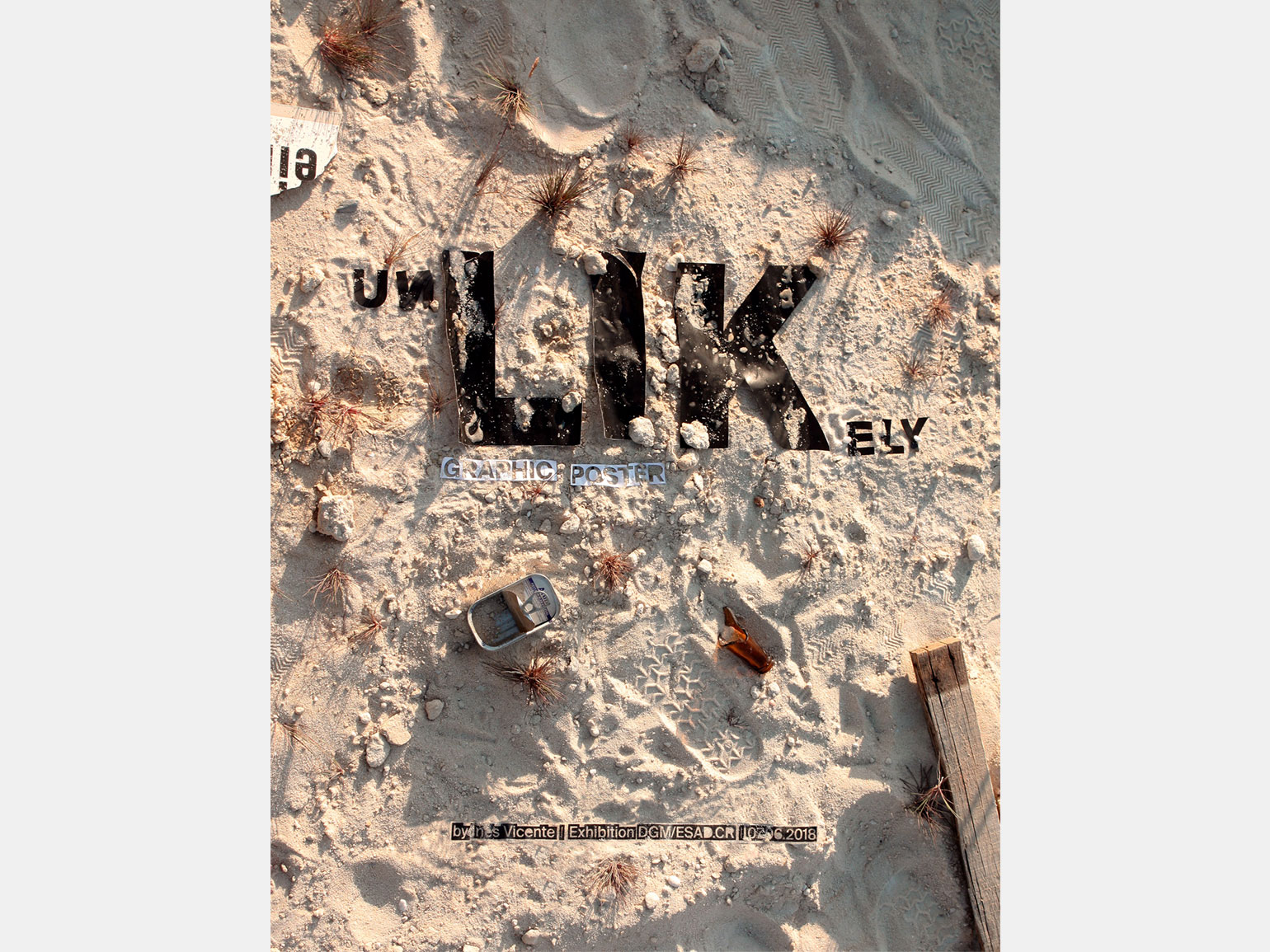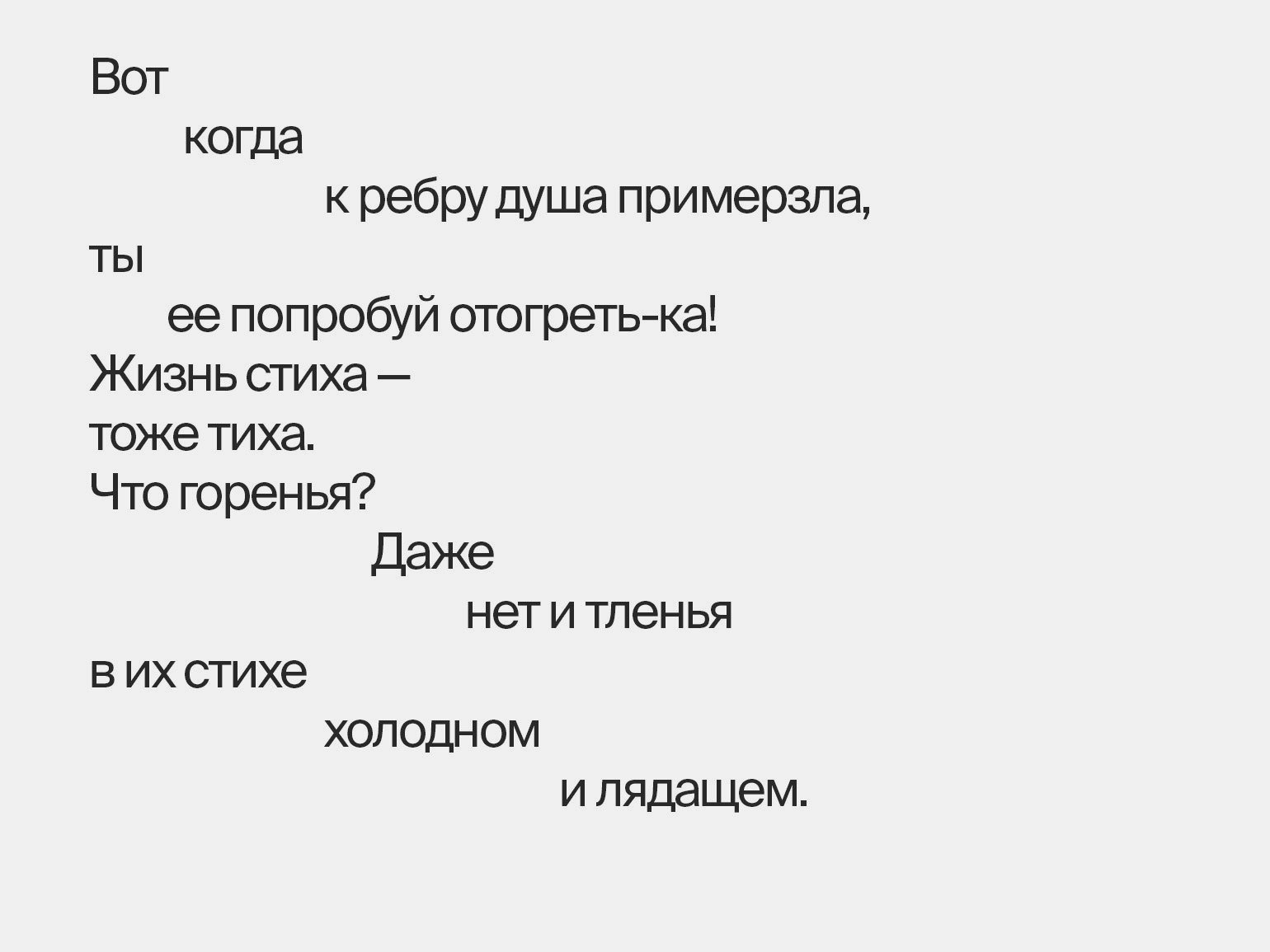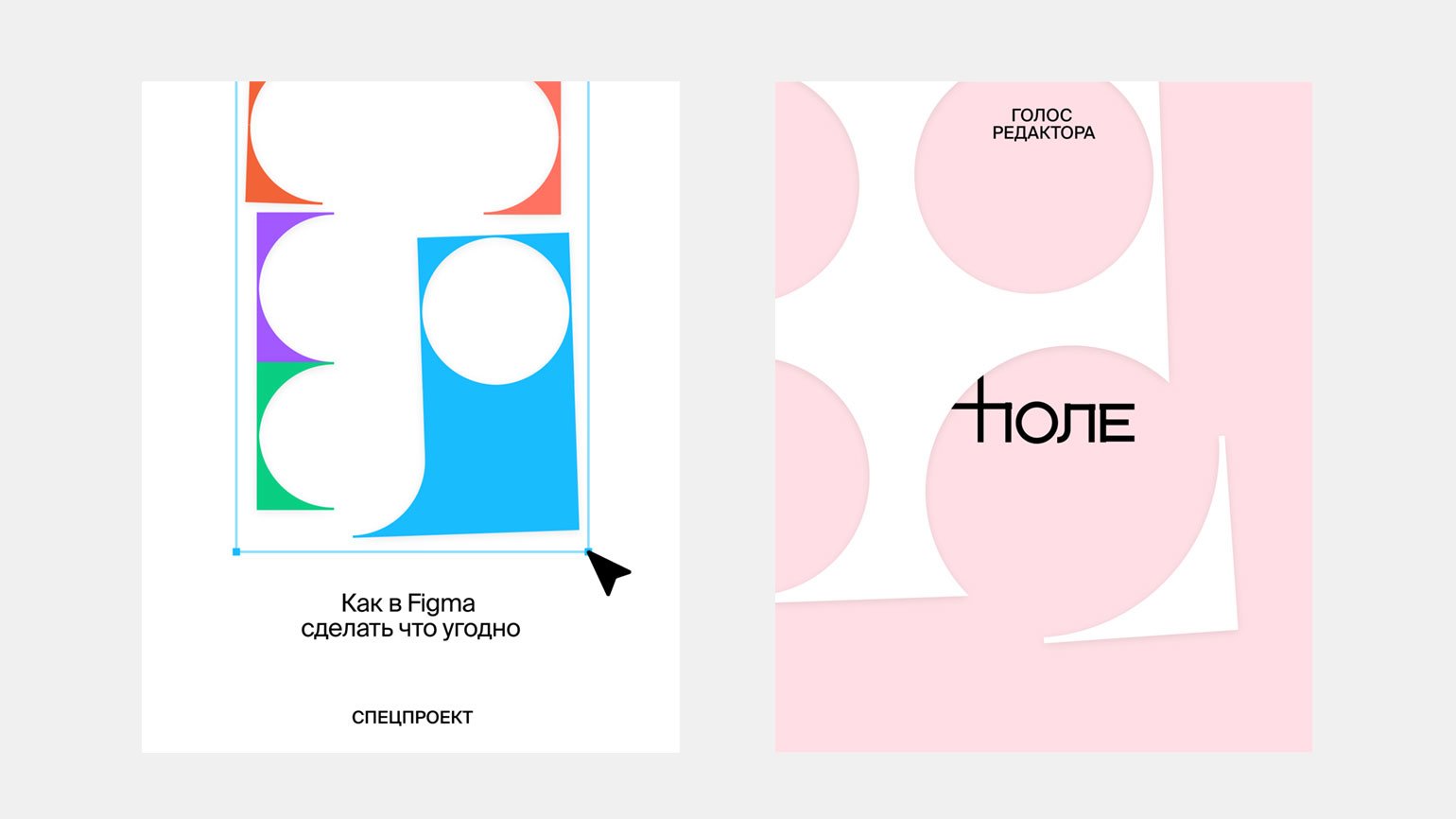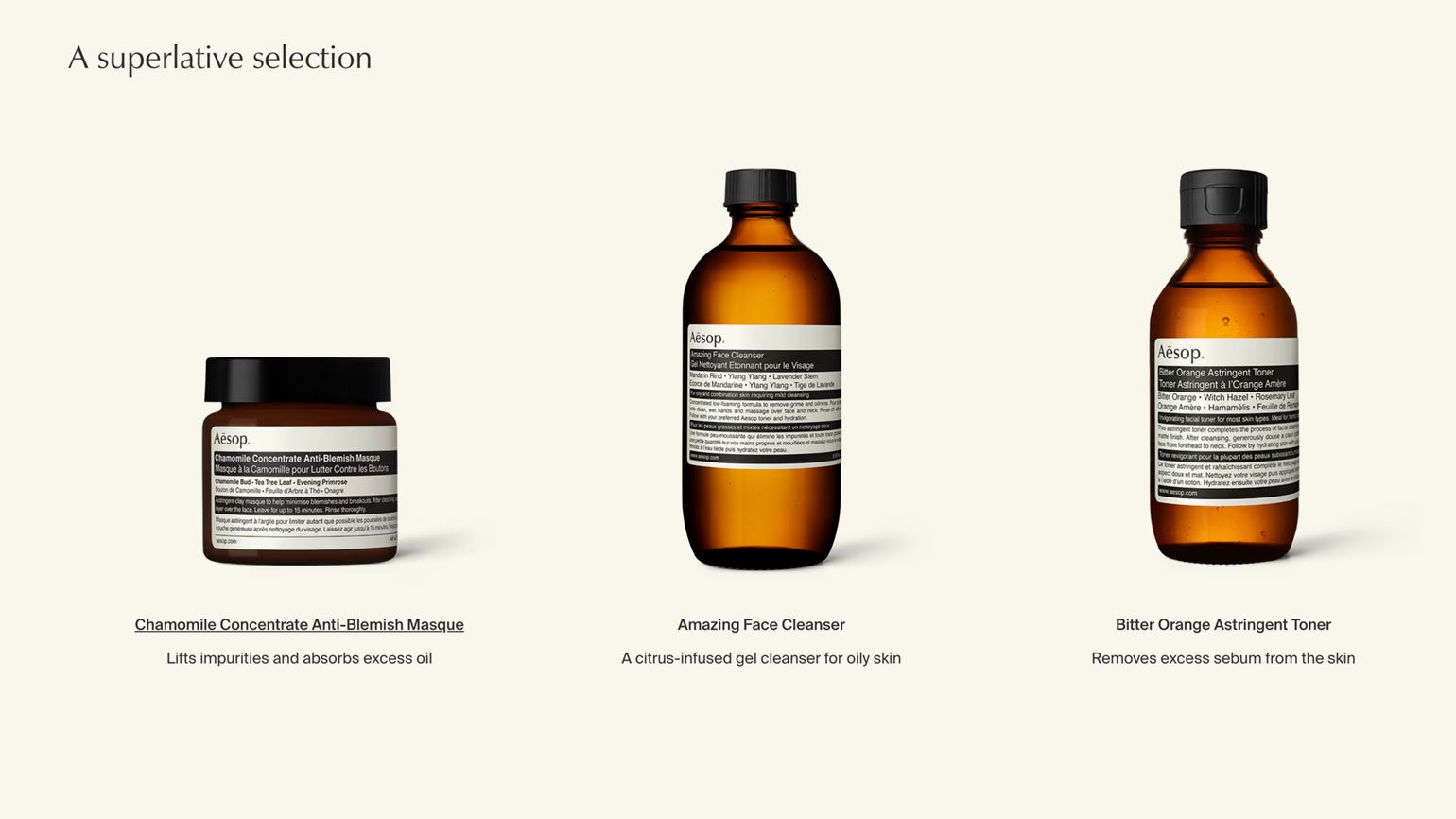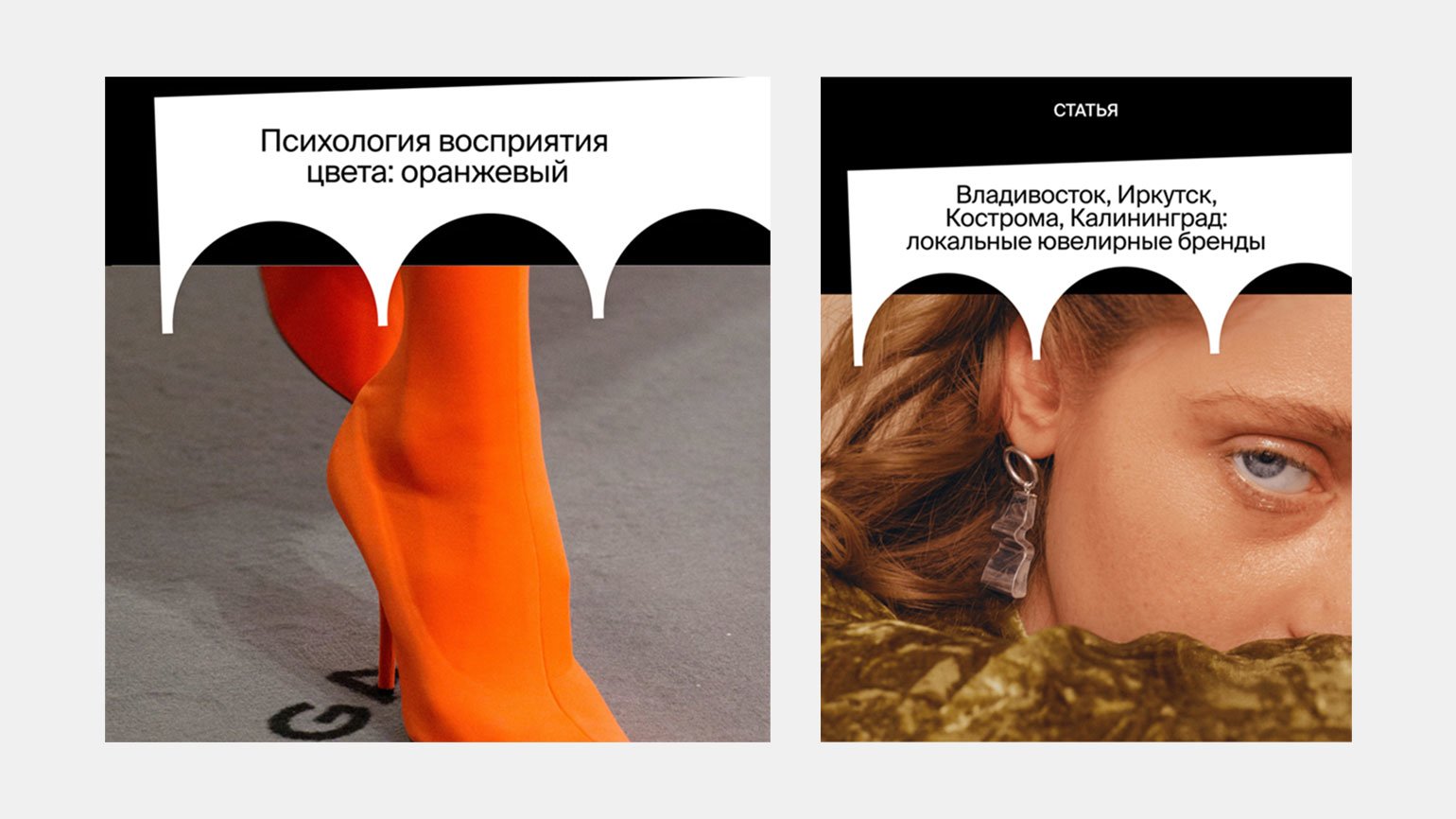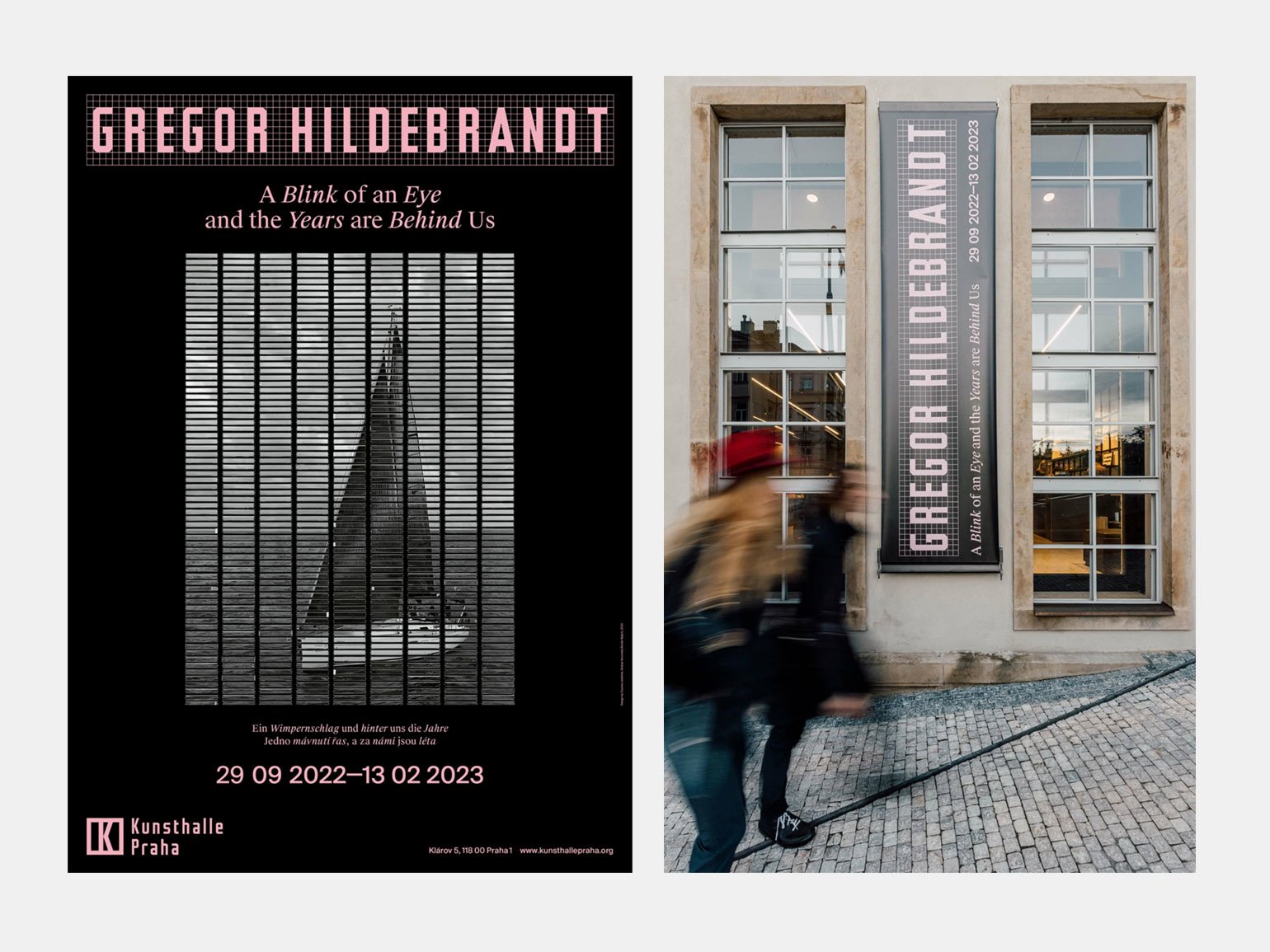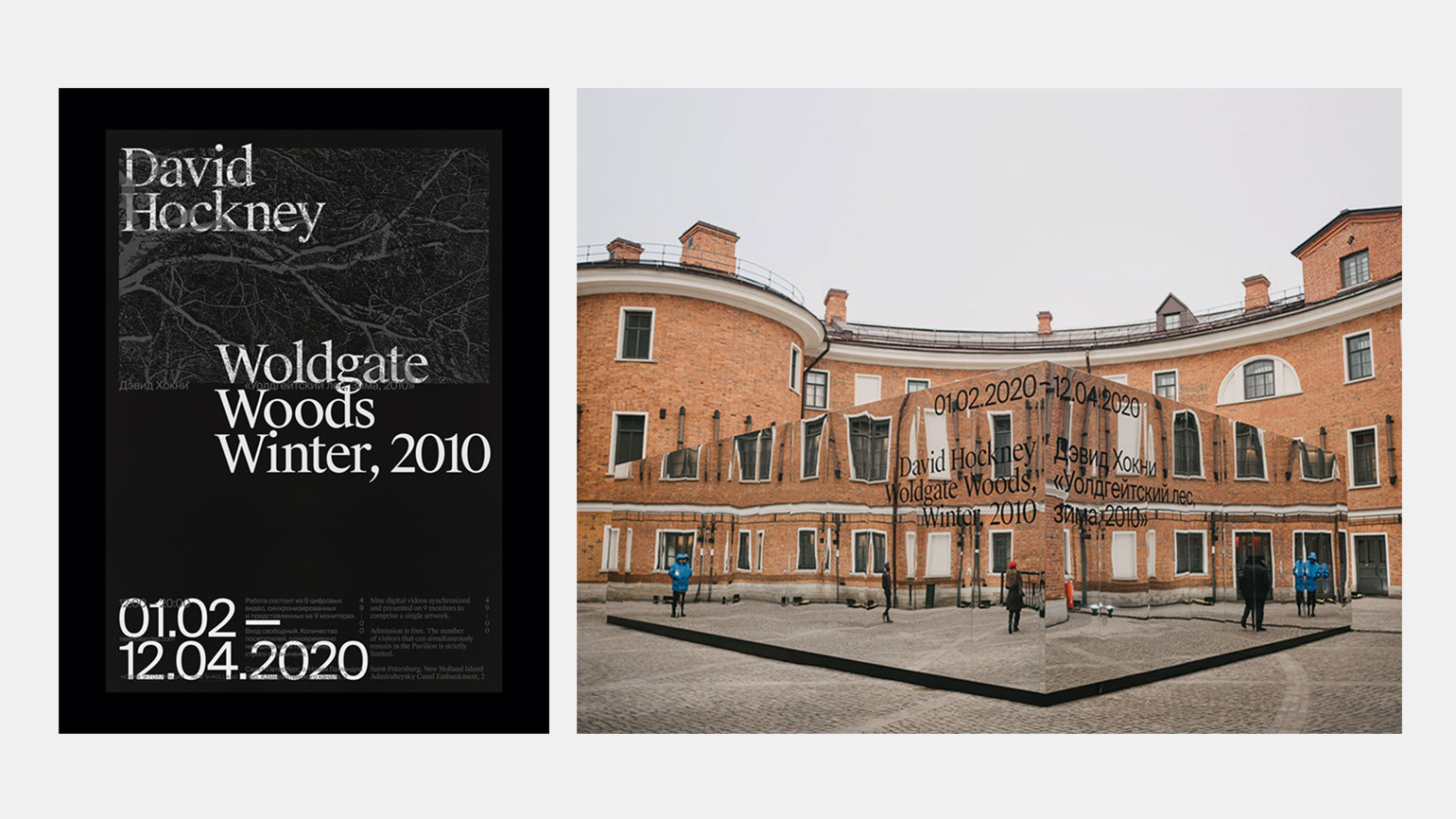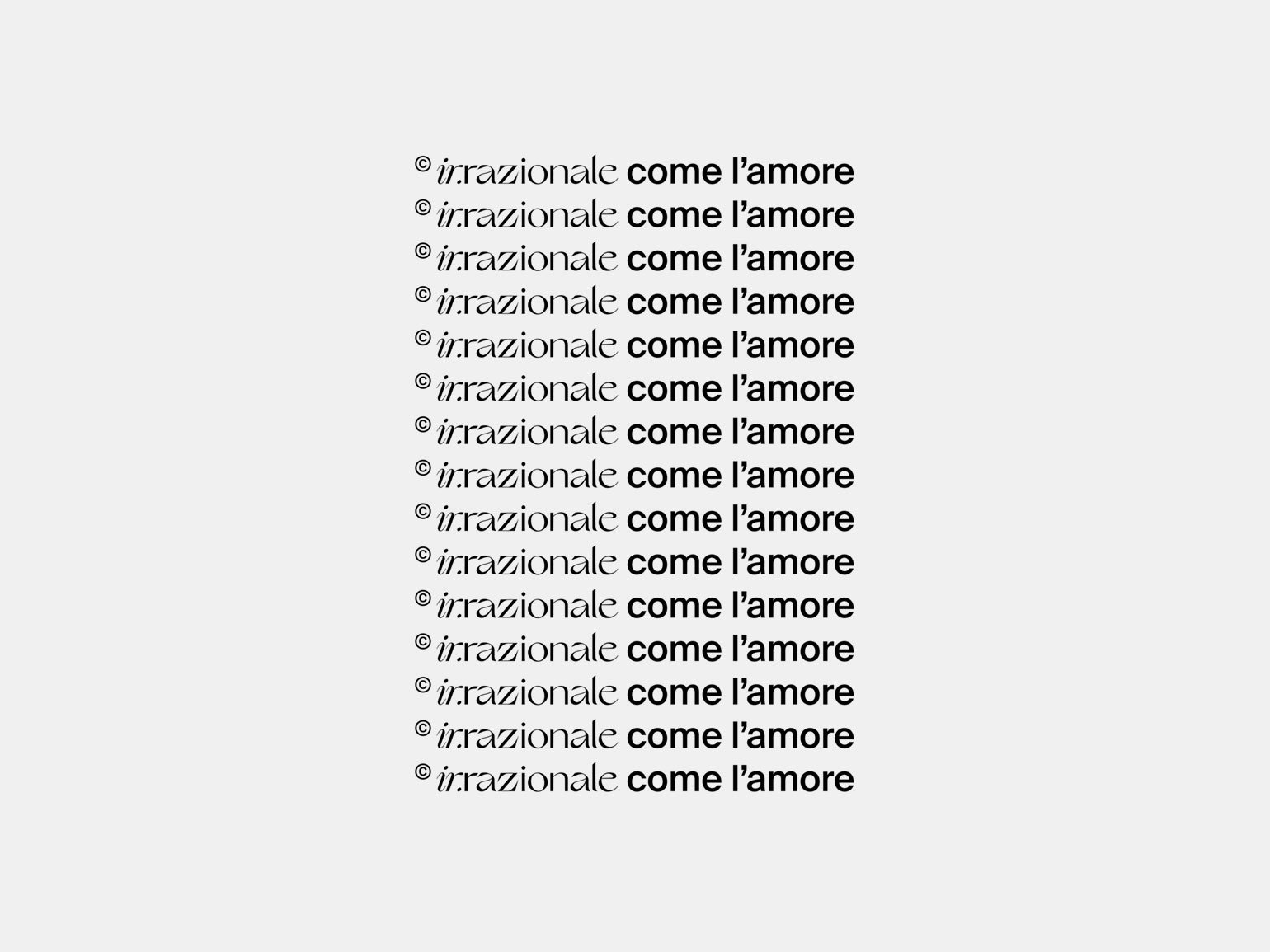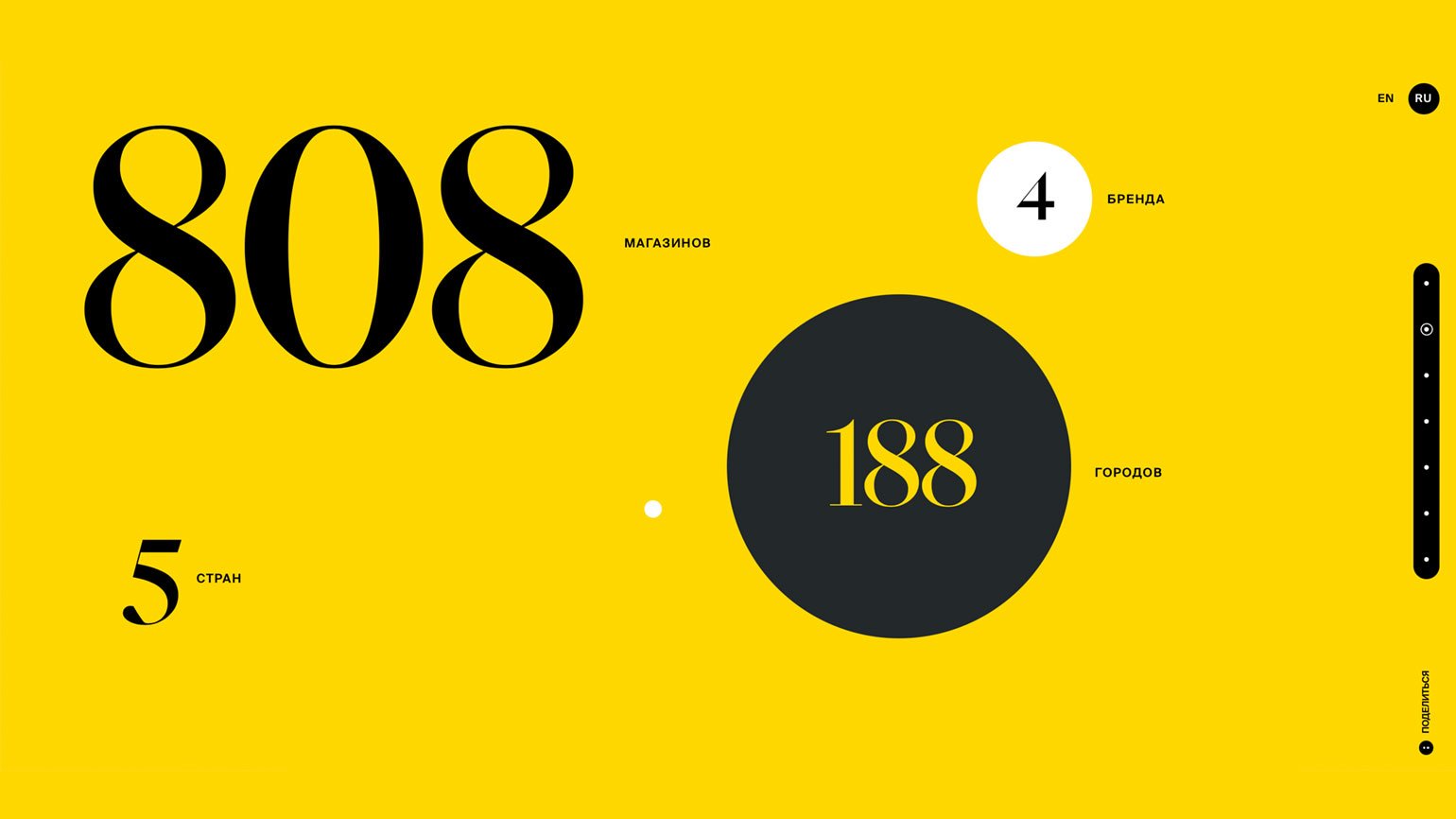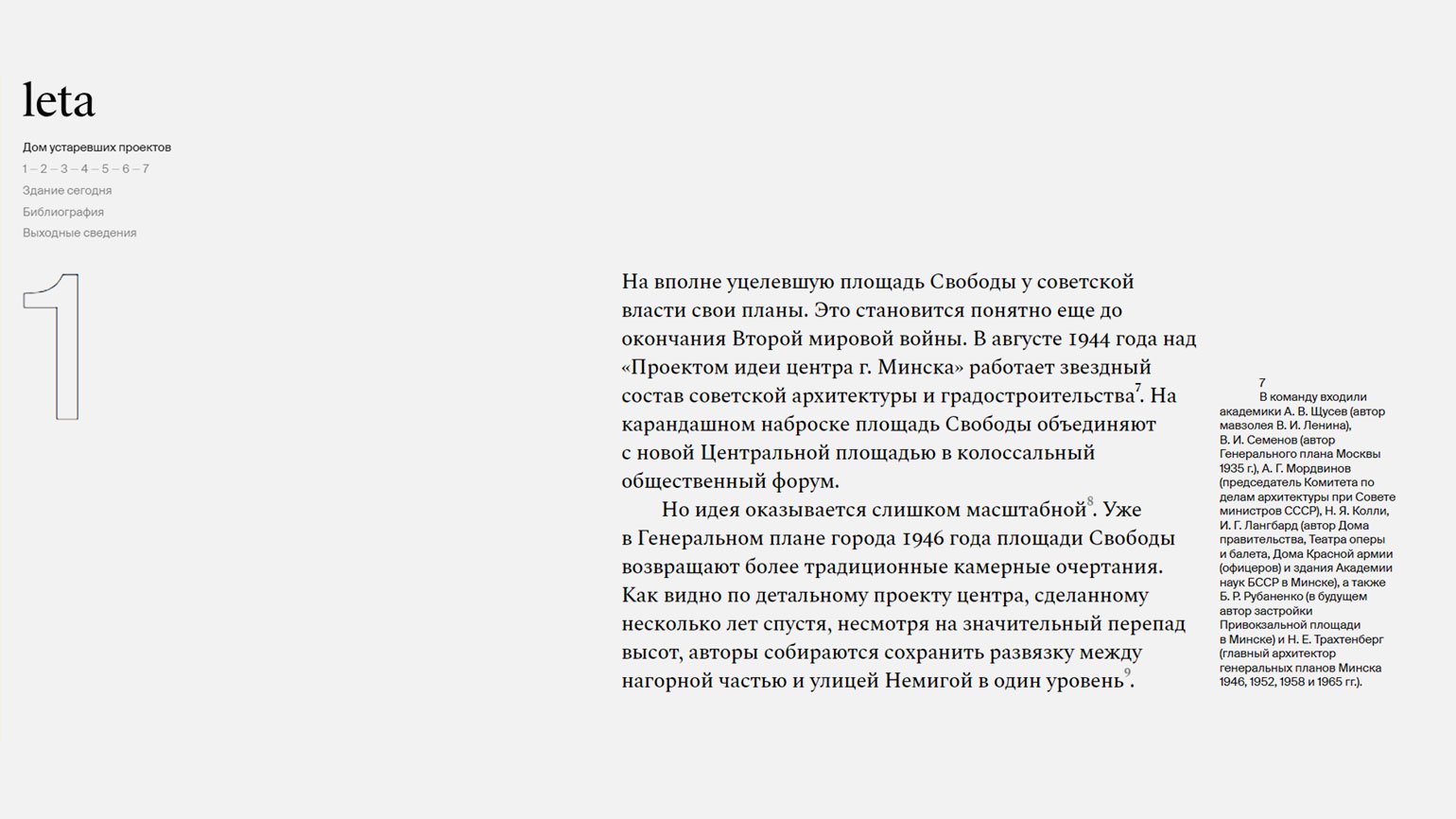
Шрифт Suisse Int’l: где используют и с чем сочетают
Рассказываем, для каких проектов подходит Suisse Int’l, и показываем примеры удачных шрифтовых пар с ним.
Изображение: Matt Benkert / Dribbble
Создать эффектную типографику для сайта, документа, постера или рекламы непросто. Правильное решение очень важно: шрифты влияют на восприятие текста и изображений, они способны и привлекать, и отталкивать. К тому же их много, и даже если для проекта уже выбран основной шрифт, к нему наверняка понадобятся дополнительные.
Разберём модную современную гарнитуру Suisse Int’l и расскажем, с чем её сочетать.
Suisse Int’l — что это за шрифт
Suisse Int’l — современный гротеск, созданный студией Swiss Typefaces. Первую его версию выпустили в 2011 году, после чего дорабатывали и дополняли.
По визуальному характеру Suisse Int’l относится к интернациональному, или швейцарскому, стилю. Это направление графического дизайна, в рамках которого стремились к «объективному» представлению информации, чистым сеткам из чётких модулей, геометричности и гуманистичности знаков. Однако графически Suisse Int’l — это не перерисованная цифровая копия шрифтов 1950-х: он напоминает модернистские швейцарские гротески, но выглядит актуально и отлично вписывается в диджитал-эстетику.
В гарнитуру Suisse Int’l входит 18 шрифтов: девять прямых начертаний от Ultralight до Black и девять соответствующих курсивов. Есть кириллица и арабский алфавит, причём разработали их носители языка — это было принципиально важно для дизайнеров из Swiss Typefaces. Кириллический набор сделали Илья Рудерман и Юрий Остроменцкий из студии CSTM, а арабский — Паскаль Зогби из 29LT.
Отрывок из стихотворения набран Suisse Int’l Book Regular
Скриншот: Skillbox Media
Suisse Int’l способен работать даже в нецифровых условиях. Чтобы сделать постер из неграфических элементов, автор обратился именно к нему: элемент unLIKely «вырезан» этим гротеском
​​Изображение: Inês Vicente NECHI / Behance
Suisse Int’l может визуально «подстраиваться» под контекст и доминировать, выглядеть и строго, и добродушно. Возможно, поэтому он стал настолько популярным инструментом графики: шрифты этой гарнитуры часто встречаются в брендинге, веб-дизайне и дизайне печатного нон-фикшена. Но особенно часто — в оформлении сайтов-портфолио студий и арт-директоров.
Фирменный стиль премиальной уходовой косметики Aesop построен на типографике со шрифтовой парой из гуманистического, слегка игривого Zapf Humanist и более ясного Suisse Int’l
Скриншот: сайт Aesop / Skillbox Media
В основе дизайн-системы сервиса 2ГИС — шрифты гарнитуры Suisse Int’l и Suisse Int’l Condensed
Скриншот: 2ГИС / Skillbox Media
Suisse Int’l — это часть суперсемейства шрифтов Suisse, в которое также входят:
• зауженный Suisse Int’l Condensed, кириллицу и греческий для которого разработал Алексей Ваняшин;
• моноширинный Suisse Int’l Mono;
• антиква Suisse Works;
• гротеск с более открытым характером Suisse Screen;
• гибридный Suisse Neue.
Посмотрим, как шрифты Suisse Int’l выглядят в разных проектах и какие шрифтовые пары с ними можно собирать.
Suisse Int’l в визуальных коммуникациях
В медиа о дизайне «поле» карточки статей оформляют Suisse Int’l Regular, Suisse Int’l Medium и Suisse Int’l Book. Типографика с ними выглядит минималистично, актуально и позволяет легко воспринимать контент.
Шрифтовая пара Suisse Int’l Regular и Suisse Int’l Book
Изображения: «поле»
Шрифтовая пара Suisse Int’l Regular и Suisse Int’l Book
Изображения: «поле»
Типографика постеров и навигации для выставки в пражском Kunsthalle построена на сложном сочетании шрифтов. Имя художника — акцидентный Kunst Grid, созданный специально для айдентики музея на основе скетча Яна Чихольда. Название «Мгновение ока, и годы прошли» на трёх языках — элегантная антиква в прямом и курсивном начертаниях. Даты выставки набраны Suisse Int’l Regular, который в таком окружении выглядит спокойным, размеренным и просто сообщает важную информацию.
Шрифтовая пара из кастомного Kunst Grid, антиквы в двух начертаниях и Suisse Int’l
Изображения: Studio Najbrt
В 2020 году в Новой Голландии в зеркальном павильоне демонстрировали видеоарт Дэвида Хокни, современного художника. Все тексты на плакатах, навигации, рекламе и на самом павильоне были оформлены парой из Suisse Int’l и родственной ему антиквы Suisse Works.
В наборе Suisse Works нет кириллицы, поэтому в адаптации дизайна на русский язык тексты набраны только Suisse Int’l. Получился эффект, будто Suisse Works «отвечает» за английский, а Suisse Int’l — за русский.
Шрифтовая пара из гротеска Suisse Int’l и антиквы Suisse Works
Изображение: Artem Strizhkov / Behance
Suisse Int’l в интерфейсах
Ян Парти создавал Suisse Int’l в диджитал-эпоху, с учётом эстетических потребностей и условий восприятия знаков, которые создают цифровые продукты. Среди прочего по этой причине шрифты этой гарнитуры широко используют в веб-дизайне.
Например, сайт в честь 15-летия российской компании Melon Group, которой принадлежат бренды Sela, Befree и прочие массмаркет-марки одежды, оформлен контрастной парой из SangBleu Empire и Suisse Int’l.
SangBleu — шрифтовая коллекция авторства дизайнеров из той же студии Swiss Typefaces. SangBleu Empire можно условно назвать романской антиквой с акцидентным характером, а сами авторы характеризуют её как «гарнитуру с синдромом Наполеона».
Шрифтовая пара SangBleu Empire и Suisse Int’l
Скриншот: сайт Melon Fashion / Skillbox Media
Ещё один пример сочетания гротеска Suisse Int’l и антиквы Suisse Works — дизайн лендинга о знаковом архитектурном объекте в Минске. Шрифтом с засечками набран основной объём текста, без засечек — примечания, заголовки и названия разделов в панели навигации. Таким образом, дизайнер использовал классическую «книжную» схему «гротеск плюс антиква» в интерфейсе.
Шрифтовая пара из гротеска Suisse Int’l и антиквы Suisse Works
Скриншот: сайт leta.today / Skillbox Media
«Агами» — производитель современной керамики с нордик-дизайном для ежедневного использования, и типографика в оформлении интернет-магазина этой марки передаёт образ спокойствия, предсказуемости и утилитарности. Тексты в элементах навигации и кнопках набраны Input Sans Narrow, графика которого отсылает к интерфейсам первых компьютеров, а описания бренда и товаров — Suisse Int’l Light, который в таком контексте выглядит мягко и миролюбиво.
Шрифтовая пара Input Sans Narrow и Suisse Int’l в начертании Light
Скриншот: сайт agami.moscow / Skillbox Media
Suisse Int’l в айдентике
Чтобы отразить в брендинге студии идею «фокуса на графическом дизайне и иррациональных эмоциях», авторы взяли акцидентный Grand Slang с дерзко-страстной пластикой букв для логотипа и нейтрально-предсказуемый Suisse Int’l в качестве поддерживающего фирменного шрифта.
Фраза «ir.razionale как любовь» оформлена шрифтовой парой Grand Slang и Suisse Int’l
Изображение: Angelo Ferrante / ir.razionale Studio / Behance
Гротеск Suisse Int’l — хороший выбор, когда нужно поддержать другие, декоративные шрифты в фирменном стиле, особенно с резкими штрихами. Его истинно швейцарская графика визуально придаёт ToV бренда спокойствие профессионализма.
Кастомный шрифт в логотипе и Suisse Int’l в качестве фирменной гарнитуры
Изображение: New Cult / дизайн студии Tuman
Suisse Int’l классно сочетается с романскими антиквами не только в дизайне интерфейсов, но и в брендинге. Например, у айдентики испанской марки обуви эксцентричных расцветок характер оптимиста: этого эффекта добились за счёт палитры ярких цветов и сочетания винтажного Bernase Roman и легкочитаемого Suisse Int’l.
Шрифтовая пара ITC Bernase Roman и Suisse Int’l
Изображение: дизайн студии Hey
Suisse Int’l в печати
Объёмная публикация Mesta иллюстраторки из Аахена Андреа Иль посвящена теме эмиграции и чувствам по отношению к покинутому дому. Она представляет собой коллекцию из 26 интервью людей разного происхождения, с разной самоидентификацией и разным восприятием их нового и старого пространства.
Основной текст набран Suisse Int’l, заголовки — Apoc, врезы — Panama, и такое сочетание различающихся шрифтов передаёт идею экспрессии и стремления смело высказаться.
Apoc, Panama и Suisse Int’l
Изображение: Andrea Ihl / Behance
Ещё один пример дизайна печатного издания — книга «Все окна настежь, а свежего воздуха нет» о культурных последствиях цифровизации. Задачей дизайнерки было создать и выдержать нейтральный тон исследования, поэтому она оформила все тексты шрифтами одного суперсемейства — Suisse Int’l, Suisse Works и Suisse Int’l Mono.
Шрифтовая пара Suisse Int’l и Suisse Works плюс Suisse Int’l Mono
Изображение: Svenja Eisenbraun
Где скачать Suisse Int’l
Единственный надёжный источник гарнитуры Suisse Int’l — это сайт словолитни Swiss Typefaces, в которой её разработали. Мы не рекомендуем обращаться к другим сайтам: на них могут быть устаревшие и некорректные версии шрифтовых файлов.
Чтобы купить Suisse Int’l на официальном сайте студии, понадобится банковская карта, выпущенная не в РФ.
В линейке Suisse Int’l все начертания платные, кроме Suisse Int’l Book: он стоит 0 франков, то есть распространяется бесплатно.
Кроме того, можно скачать весь пакет без оплаты для пробного использования. Например, чтобы протестировать, подходят ли шрифты Suisse Int’l для логотипа или интерфейса.
Шрифтовая пара из бесплатного Suisse Int’l Book и платного Suisse Int’l Regular
Скриншот: Saint Louvent / Skillbox Media
Аналоги Suisse Int’l
Если Suisse Int’l не подходит по графике или стоимости, можно обратиться к другим семействам «интернациональных» шрифтов:
• бесплатный Inter из каталога Google Fonts;
• неогротеск Acumin, который можно бесплатно установить из библиотеки Adobe Fonts;
• великий образец швейцарского шрифтостроения Univers;
• близкий родственник «гельветики» Haas Unica;
• вариативный Basel Grotesk;
• чуть более винтажный Graphik.